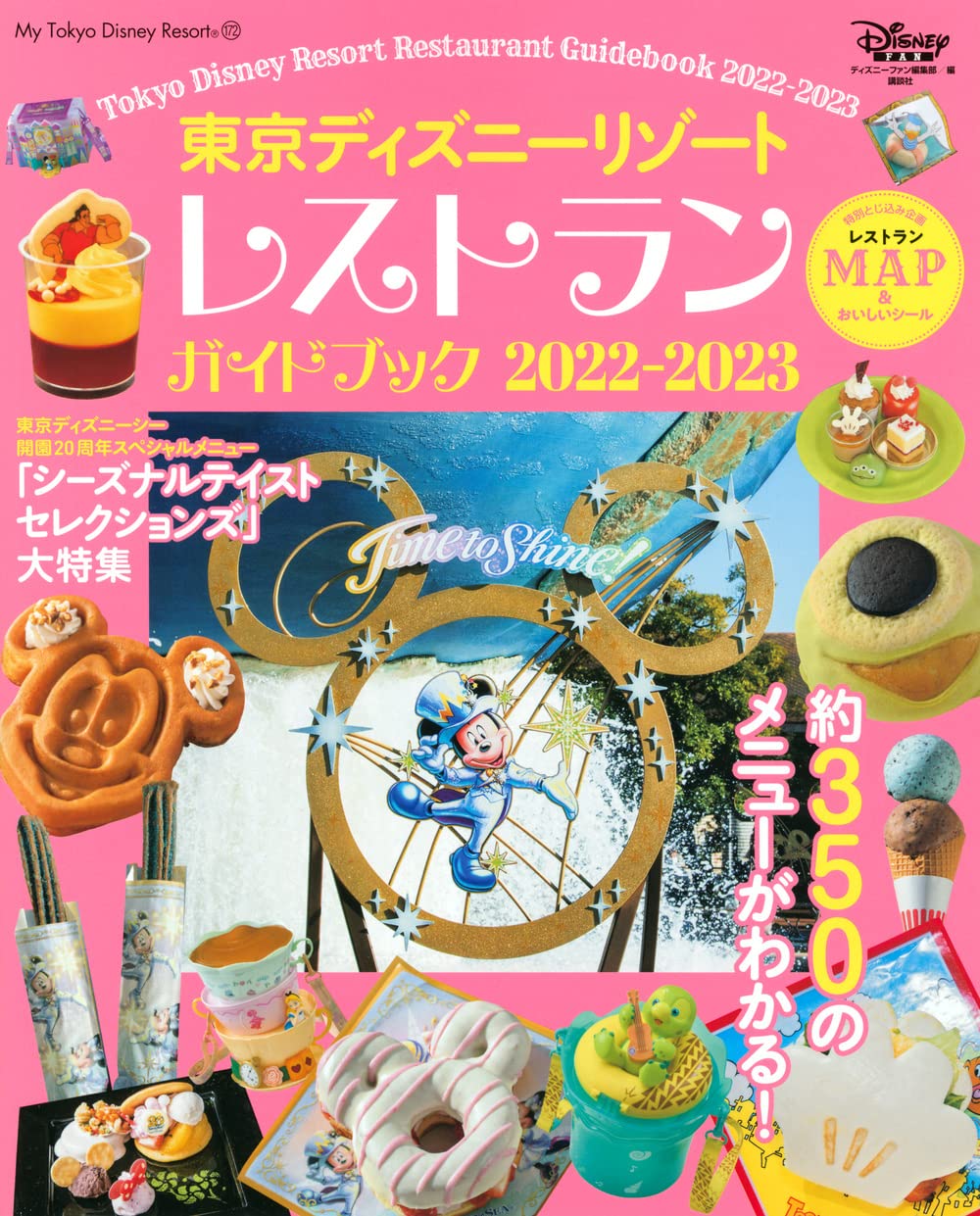
えほん さとうゆたか
書名:クリスマスのまえのよる
著者:クレメント・C・ムーア、ラクエル・マーティン
発行:大日本絵画
保護猫カフェ さとうゆたか
ねこかつ。
ロゴ部分。
しかけえほん さとうゆたか
書名:くるみわり人形
著者:リリー・マッカードル、ボディル・ジェーン
発行:大日本絵画
あ さとうゆたか
楽譜集のようだ。
書名:NHKキッズソングベスト50
発行:NHK出版
ハロウィン さとうゆたか
ハロウィンとかクリスマスとかバレンタインとかの時期に、良く使われるね。
サプリの広告 さとうゆたか
サプリメントの広告画像。
セブン−イレブン takumi
セブン-イレブンに掲示されていた「カレーフェス」の告知です。
少し加工されていますね。
やはり、この書体とカレーは、相性がいいんですね…。
あ さとうゆたか
書名:けっこう不思議な日常10
著者:吉野奏美
発行:三栄書房
デコ文字 さとうゆたか
好きな文字を1文字ずつ打てます。
LINEの絵文字(デコ文字)。